モリサワフォント2017年新書体がリリース開始
モリサワは11月8日に予定されていたMORISAWA PASSPORT製品のすべての契約者に向けた「MORISAWA PASSPORT アップグレード2017」を予定通り執り行い、2017年の新書体の無償提供を開始した。
株式会社モリサワは、2017年11月8日(水)よりMORISAWA PASSPORT 2017年新書体のダウンロード提供を開始すると発表した。
提供となる新書体はモリサワフォント17書体とヒラギノフォント6書体とAP-OTF版7書体。
A1ゴシック
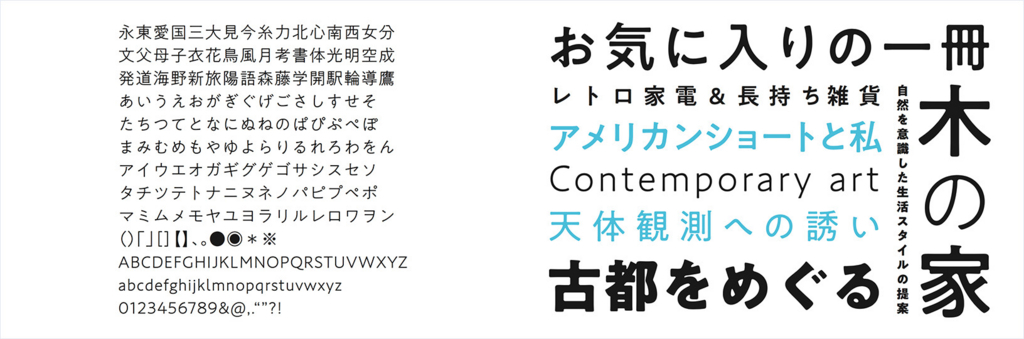
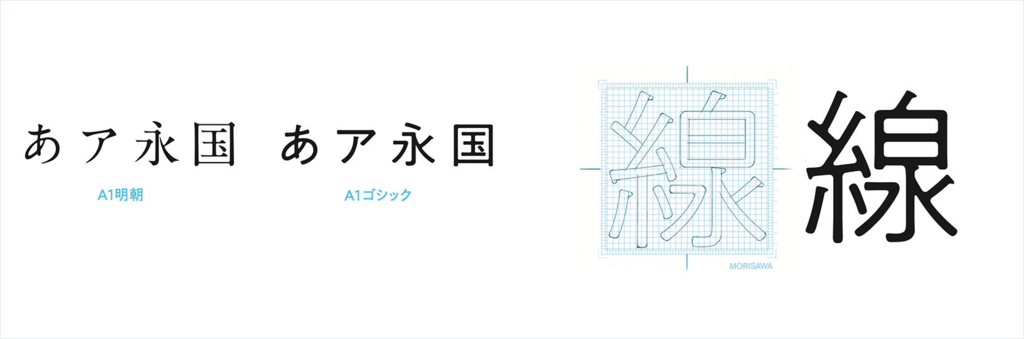
A1明朝の基本となる骨格を参照して作成された、オールドスタイルのゴシック体ファミリー。線画の交差部分の墨だまり表現や、エレメントの端々に僅かな角丸処理を加えることで、温もりのあるデザインに仕上げる。LからBまで4つのウエイトで展開。
Citrine
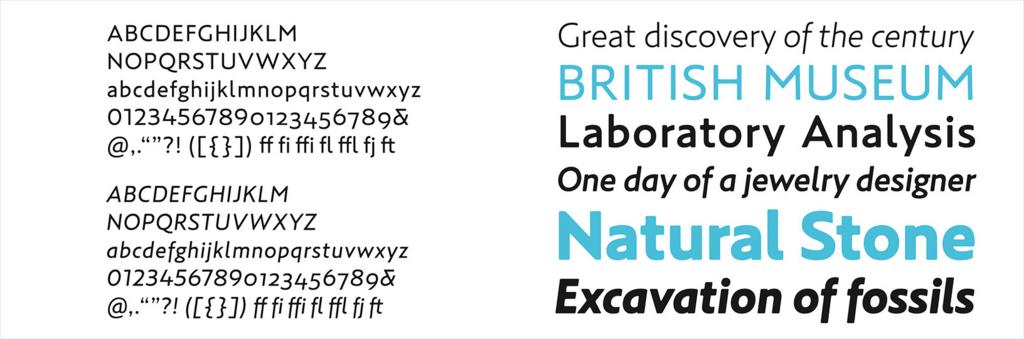
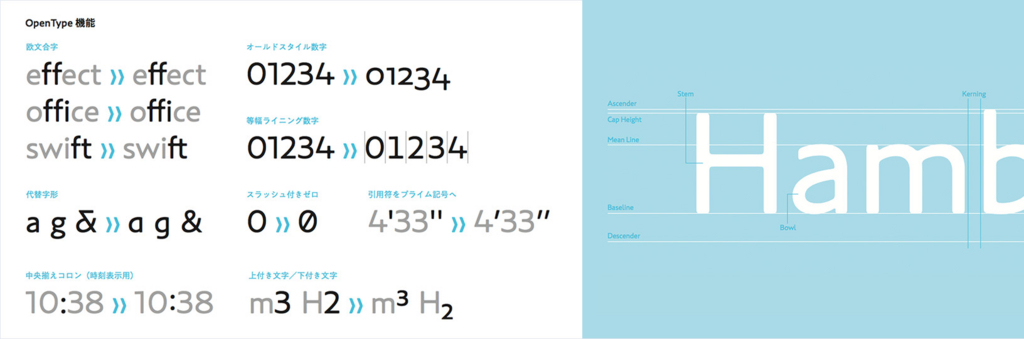
20世紀初頭の活字から影響を受けたサンセリフで、明るく幾何学的な要素を取り入れつつも、レトロで優しい風合いをもつヒューマニストサンセリフを目指して作成された。A1ゴシックとの和欧併記を目的に作られており、墨だまりや角丸処理といった共通のエレメントを採用されている。
みちくさ
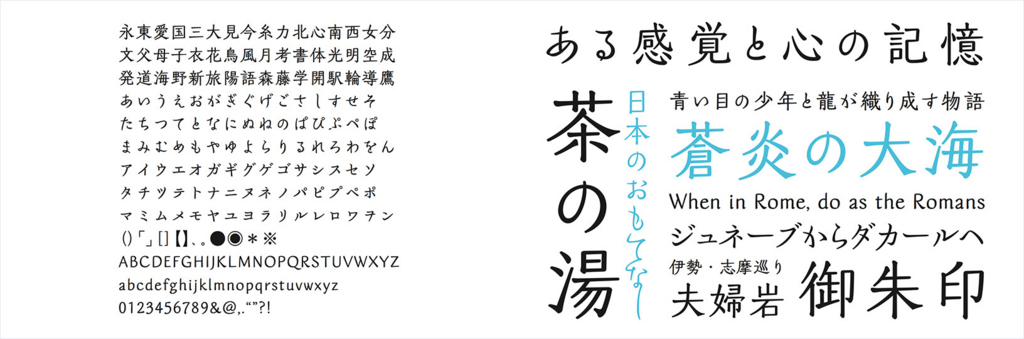
ふところを絞った骨格と、やわらかく現代的なエレメントから構成される明朝体風のデザイン書体。独様な連綿体や代替字形が用意されており、OpenType機能を使用することで、縦組みの際に文脈を考慮した連綿体などを呼び出すことができる。
連綿体
続け字の書体。欧文書体のスクリプト体に相当。元々は手書き書体であり、行書体ベースのものと、草書体ベースのものが存在していたがモリサワフォントのみちくさは明朝体での連綿体になっている。
きざはし金陵
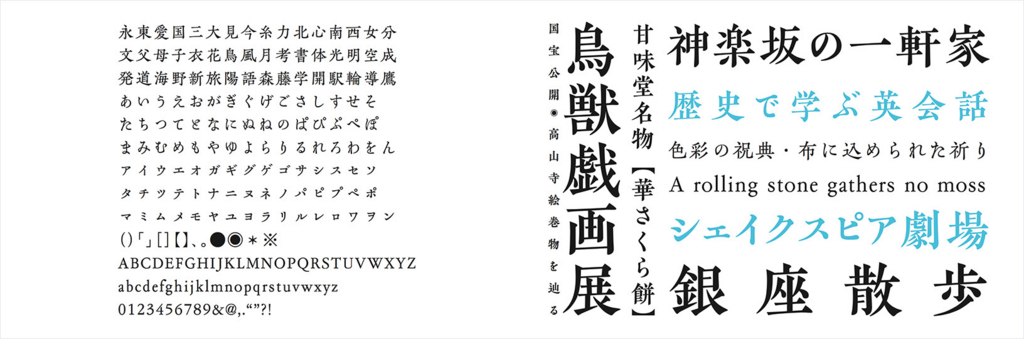
中国・明代の南京国子監で刊行された「南斉書」を元に復刻した「金陵」と、1893年に東京築地活版製造所で印刷された「長崎地名考」を元に復刻した和字(かな)書体「きざはし」をマッチングした書体。線画や骨格を画一的に整備した近代の明朝体とは一線を画す、正統派のオールドスタイルの明朝体。
秀英にじみ明朝
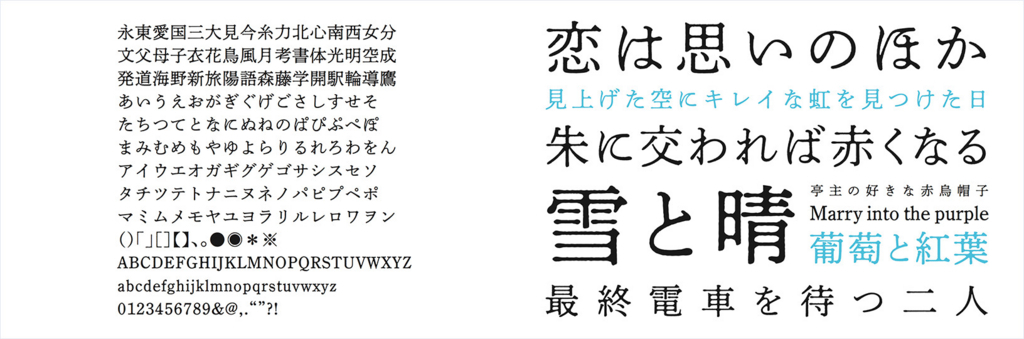
2009年にリリースされた「秀英明朝L」をベースに、活版印刷による紙面上でのインクのにじみを再現した書体。線画にランダムな揺らぎや太み、丸み処理を施すことで、やわらかい印象をもったアナログ感やレトロ感を演出する。
黒曜
見出し用に作成された、豪快でたっぷりとした黒みをもつデザイン書体です。大胆な筆使いによる「はね」や「はらい」、線画の太細のコントラストが特徴。無骨で力強いイメージを表現したいシーンや、題字などの大見出し、看板サインなどの利用に最適。
Hiragino Sans TC
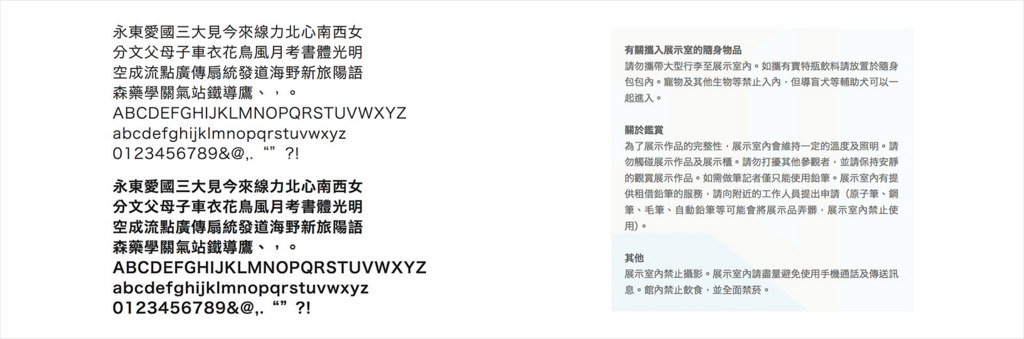
和文書体「ヒラギノ角ゴ」のデザインを踏襲した、ゴシック体の繁体中文です。台湾、香港、マカオで使用される繁体字を現代的なデザインの書体として仕上げている。和文書体の「ヒラギノ角ゴ」、「ヒラギノ角ゴ 簡体中文」と合わせて使用すれば、日本語・簡体中文・繁体中文を併記する際も、統一感のあるデザインが可能。